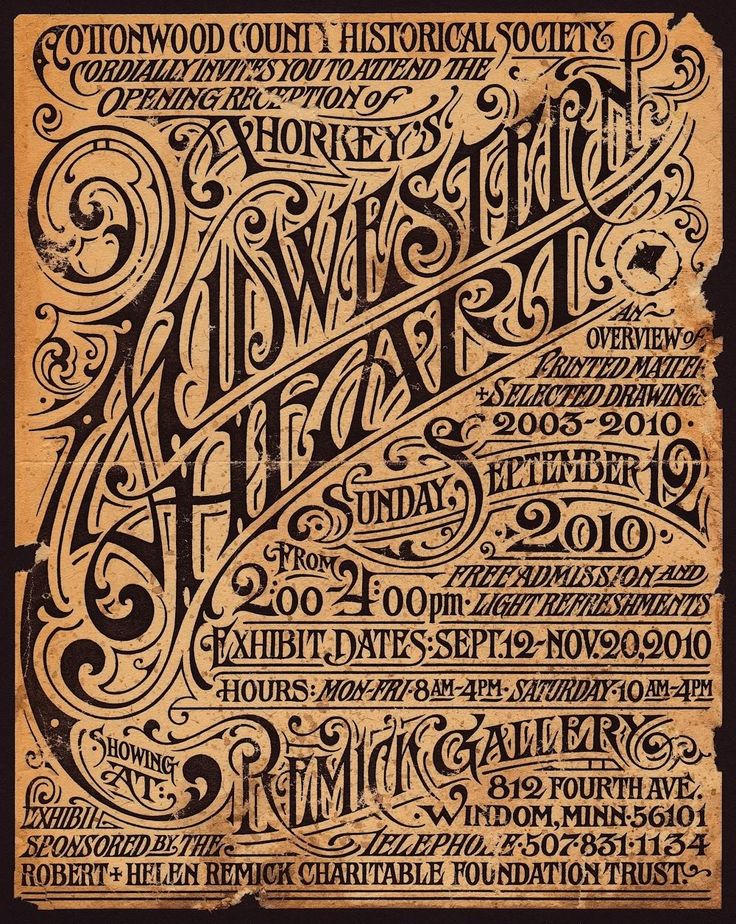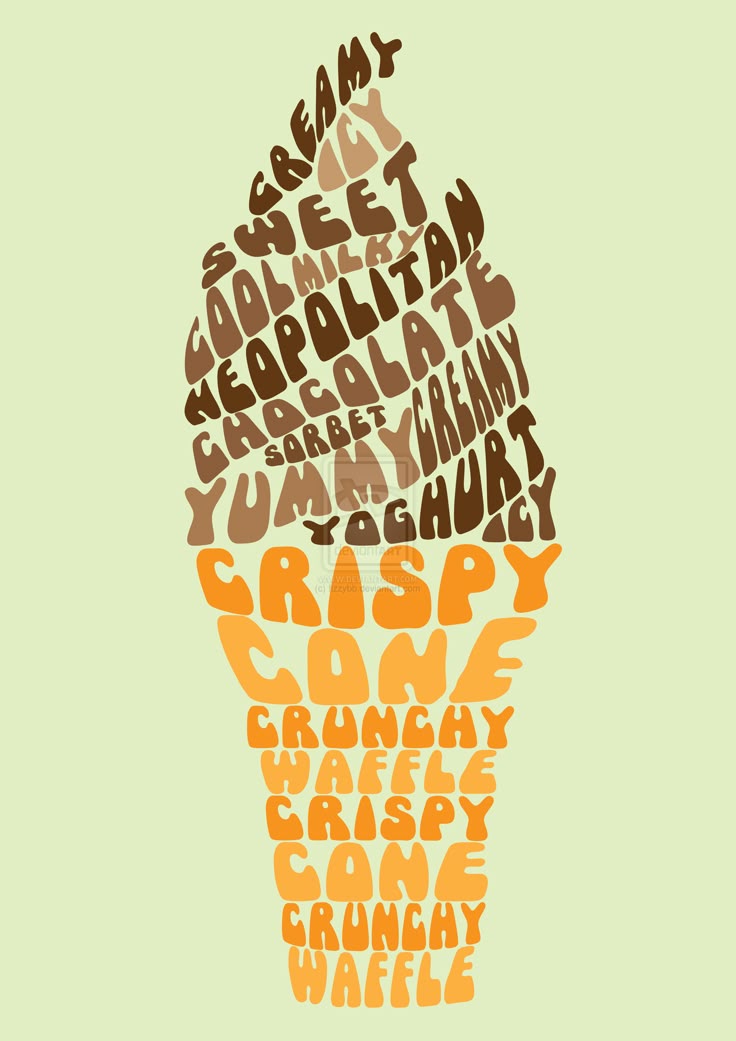
Шрифты в рекламе | Блог LiveDune
Как выбрать подходящий шрифт для рекламы в соцсетях
Представьте, что в мире существует только один шрифт и все вывески, журналы, названия брендов и так далее написаны этим шрифтом. Например: Google, Amazon, Canon, Ebay, Disney.
В первом случае потерялась вся индивидуальность: нет отличительных черт для узнаваемости, нет характера. В этом и есть главная роль шрифтов в тексте ― придавать уникальность и влиять на эмоциональное восприятие.
Большое влияние шрифт текста оказывает в рекламе. От него может зависеть конверсия и эмоциональная окраска рекламного объявления. Например, если текст на креативе нечитабельный, то человек не сможет ознакомиться с вашим предложением или не поймет его и уйдет, не совершив никакого действия. То есть конверсия объявления будет низкая.
Классификация шрифтов
Существует множество шрифтов, но все их можно отнести к 6 категориям.
Каждая категория имеет свою уникальную черту.
Так как реклама должна быстро и четко восприниматься, избегайте «Рукописных», «Леттеринга» и «Акцидентных» шрифтов. Их сложно читать и не каждый человек захочет уделить этому время и усилия.
Универсальный вариант ― шрифты без засечек. Они несут в себе позитивную дружелюбную энергетику и легко воспринимаются, поэтому считаются лучшим шрифтом для чтения в онлайн. Единственный минус ― в них нет ярко выраженной индивидуальности.
Шрифты должны обязательно сочетаться со сферой бизнеса. Например, мультяшные шрифты по типу Comic Sans не подойдут для таких серьезных сфер, как недвижимость или юриспруденция, т.к. не несут в себе надежность и серьезность.
Эксперименты восприятия шрифтов
Нашли несколько интересных исследований шрифтов и их восприятия, которые помогут понять, как правильно использовать шрифты, чтобы увеличивать конверсию рекламного объявления.
Эксперимент Д. Эльбрехт
Д. Эльбрехт провел свое исследование еще в 20 веке, в ходе которого выявил, что слова, выделенные жирным шрифтом и/или курсивом, воспринимаются дольше, чем обычные слова. Это связано с выработанной привычкой ― в типографике с давних времен таким образом выделяются важные фразы. Именно поэтому человек затрачивает больше усилий и времени для распознавания смысла выделенного текста.
Какие выводы сделать: в рекламном тексте можно выделить главный смысл (преимущества, размер скидки и так далее) фразы жирным или курсивом. Главное ― не переусердствовать, выделять только короткие фразы или заголовки.
Эксперимент The New York Times
Отдельный интерес вызывают исследования эмоционального восприятия шрифтов. Например, New York Times в 2012 году провел эксперимент, где участникам нужно было определить, правдивая или ложная информация в предложении. В эксперименте участвовали 6 шрифтов ― три с засечками (Baskerville, Computer Modern или Georgia) и три без засечек (Trebuchet, Helvetica или Comic Sans).
Итоги эксперимента показали, что традиционному шрифту с засечками ― Baskerville доверяли больше, чем шрифту без засечек ― Comic Sans. И The New York Times пришел к выводу, что шрифты с засечками являются более формальными и несут в себе «надежность», поэтому им доверяют. А вот шрифты без засечек ― неформальны, но зато более дружелюбные.
Количество человек, которые посчитали текст, написанный определенным шрифтом, правдой.
Какие выводы сделать: шрифты способны вызывать подсознательные ассоциации, поэтому выбирая шрифт для рекламной кампании, важно соотнести сферу бизнеса и настроение, которую несет шрифт (смотреть таблицу выше).
Эксперимент рекламной компании Yieldmo
В 2015 году компания протестировала три шрифта с засечками и три шрифта без засечек на более 2 миллионах человек в мобильной сети, что в 44 раза больше, чем в предыдущем эксперименте New York Times. Цель ― определить эффективность каждого шрифта по кликабельности рекламных объявлений.
В исследовании участвовали следующие шрифты: Helvetica, Arial, Verdana, Times New Roman, Georgia и Garamond.
После подсчета результатов Yieldmo были очень удивлены, так как считали, что шрифты Arial и Helvetica неопытному глазу кажутся одинаковыми, а по результатам исследования они показали разную эффективность.
Лучшие результаты показал шрифт Times New Roman ― CTR в объявлениях с этим шрифтом возрос на 15%. Шрифты Arial и Georgia также показали хорошие результаты, что не скажешь про шрифт Garamond ― он продемонстрировал самый низкий результат из всех. Исходя из итогов исследования, компания Yieldmo заменила шрифт во всех своих объявлениях на Times New Roman.
Какие выводы сделать: при тестировании разных групп рекламных объявлений экспериментируйте не только с креативами, текстом и настройками, но и со шрифтами. Не факт, что Times New Roman будет для вас выигрышным, но как минимум протестировать шрифт с засечками и без засечек однозначно стоит.